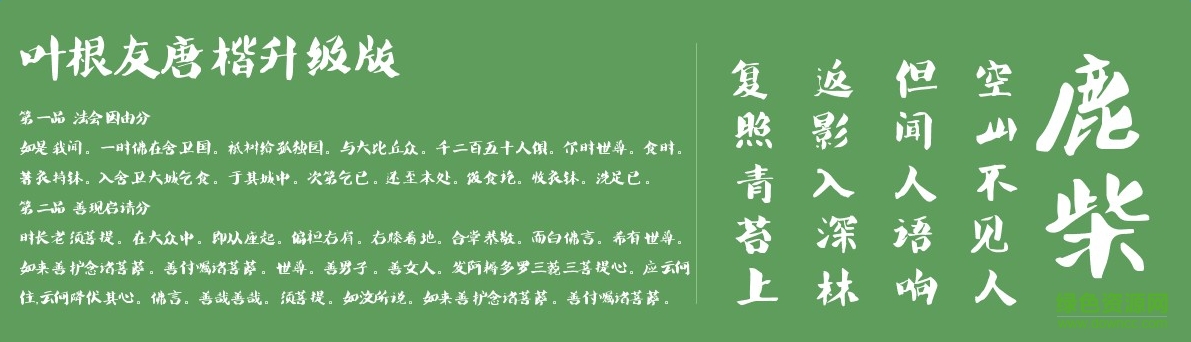
葉根友唐楷升級版
葉根友唐楷升級版字體是由中國書法奇人,五筆同書世界首創(chuàng)者,連筆空心字吉尼斯世界紀(jì)錄保持者葉根友先生親自書寫的一款字體,是葉根友先生平時書寫最多的一種,也是最為實用的風(fēng)格。字體大方,流暢。歡迎下載!
葉根友唐楷升級版字體
葉根友唐楷簡是特楷字體的姊妹風(fēng)格字體,在延續(xù)特楷字型基礎(chǔ)上重新創(chuàng)意,整個字型較之前的特楷更加嚴(yán)謹(jǐn),風(fēng)格遒勁,自然而不失灑脫,是一款標(biāo)題用字不錯的選擇。